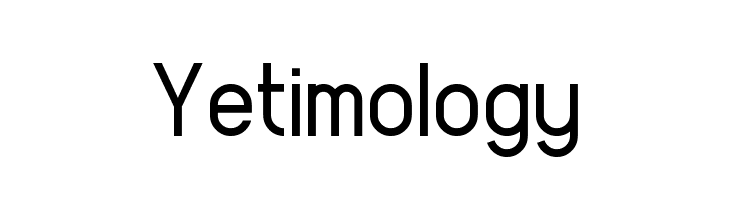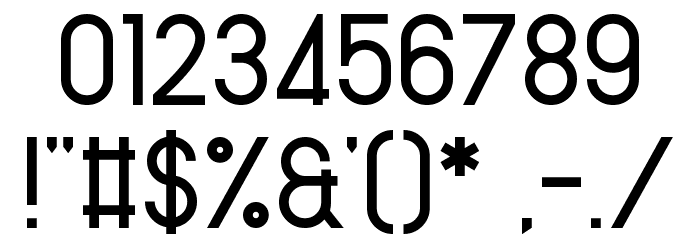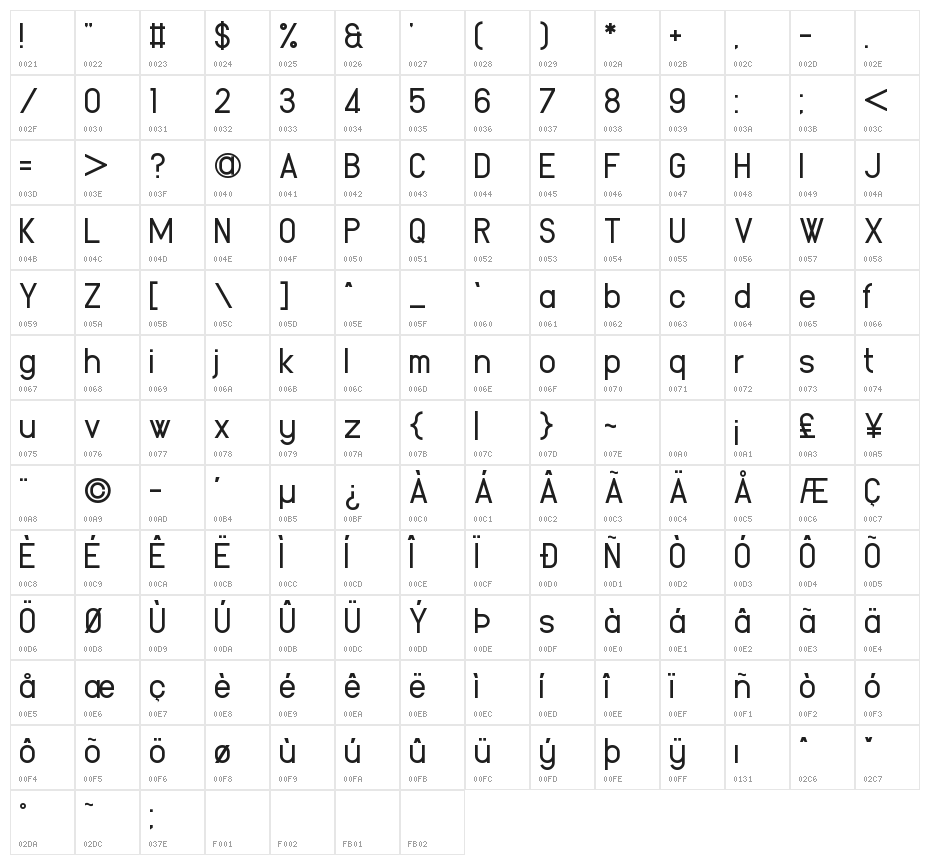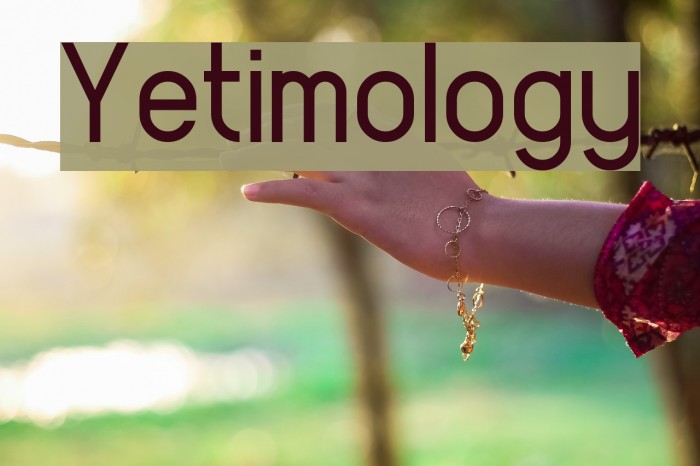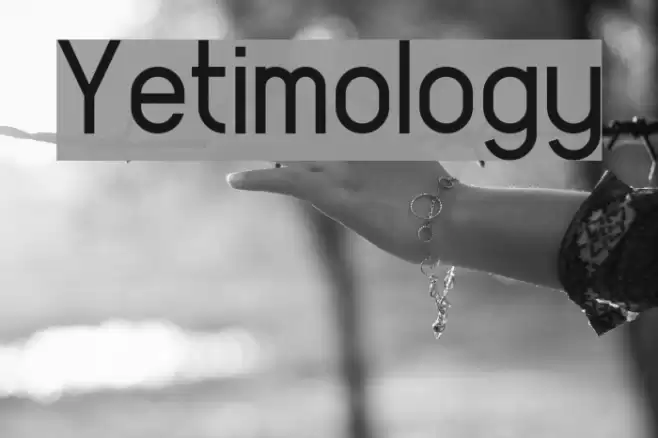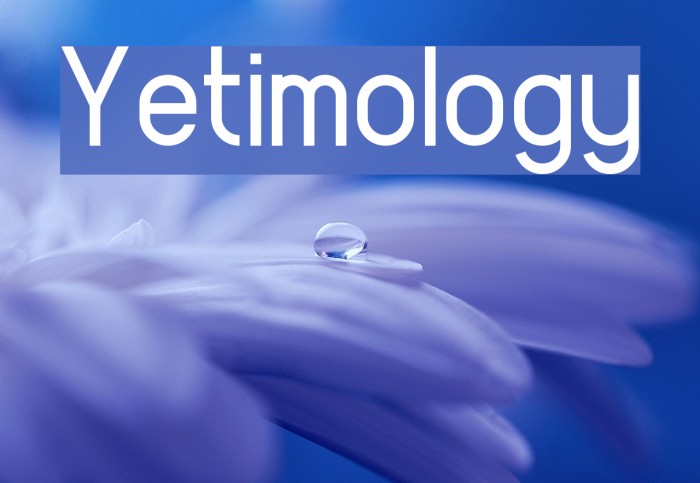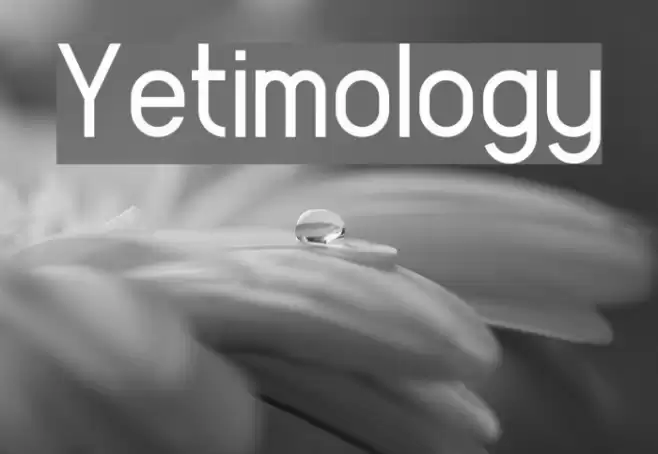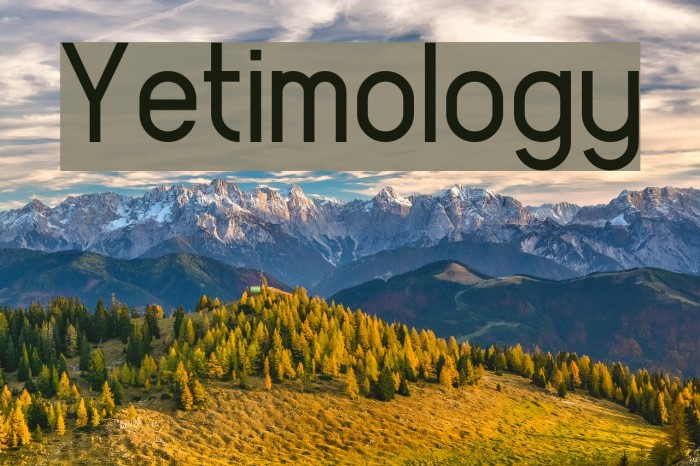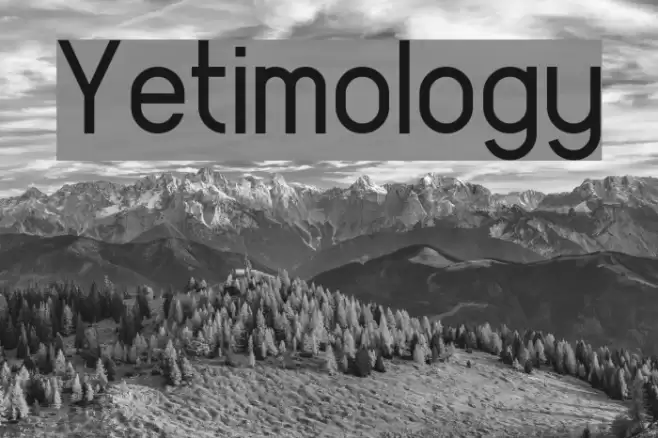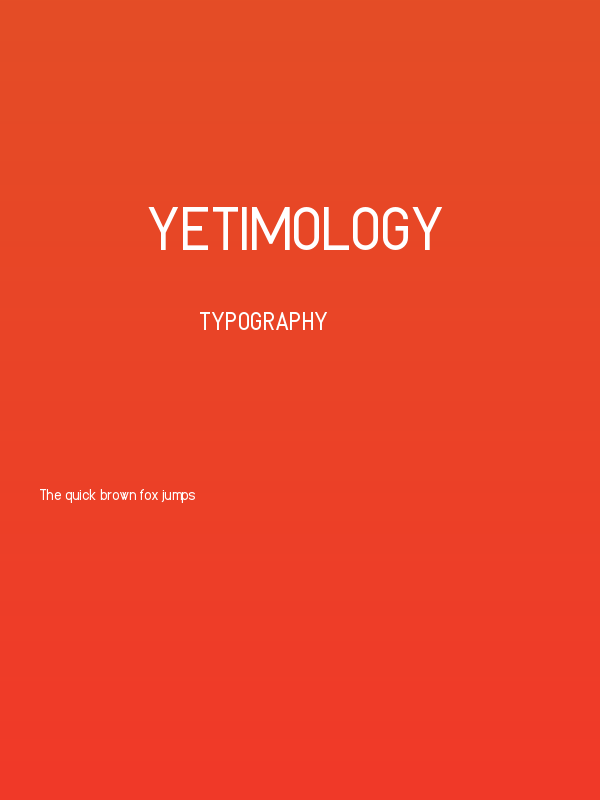
Yetimology Font
YETIMOLOGY MAIUSCOLE
YETIMOLOGY MINUSCOLO
YETIMOLOGY ALTRI CARATTERI
| Progetti proposti | Ideal for branding, web design, advertising, and editorial layouts due to its clarity and modern aesthetic. |